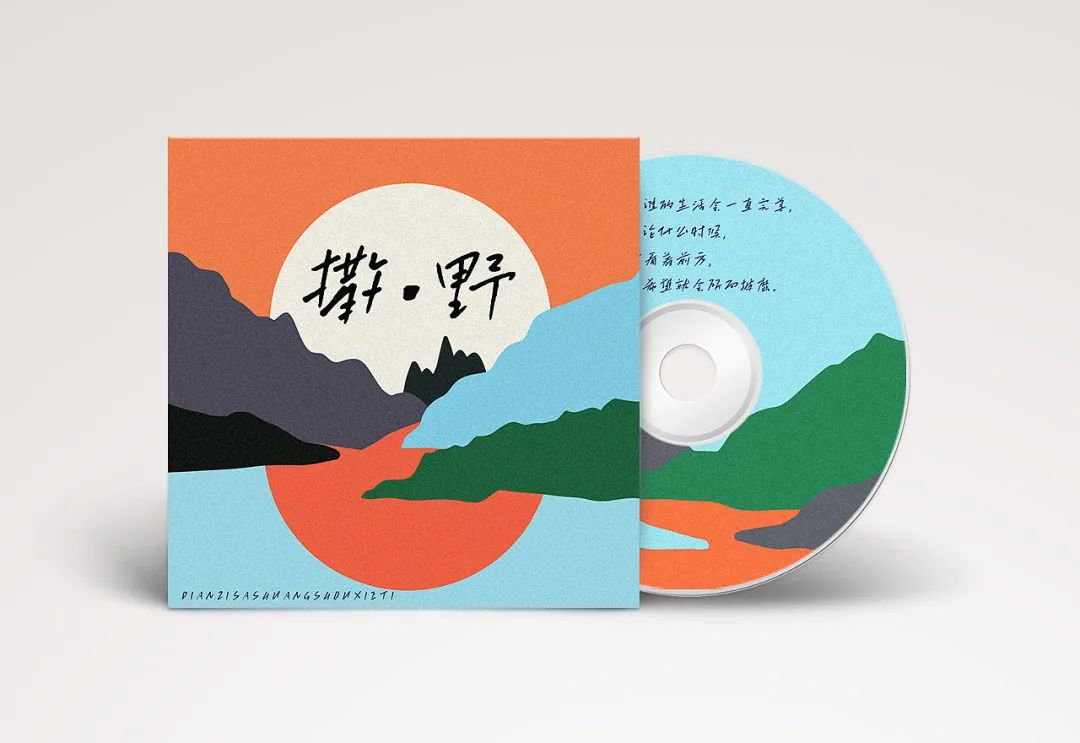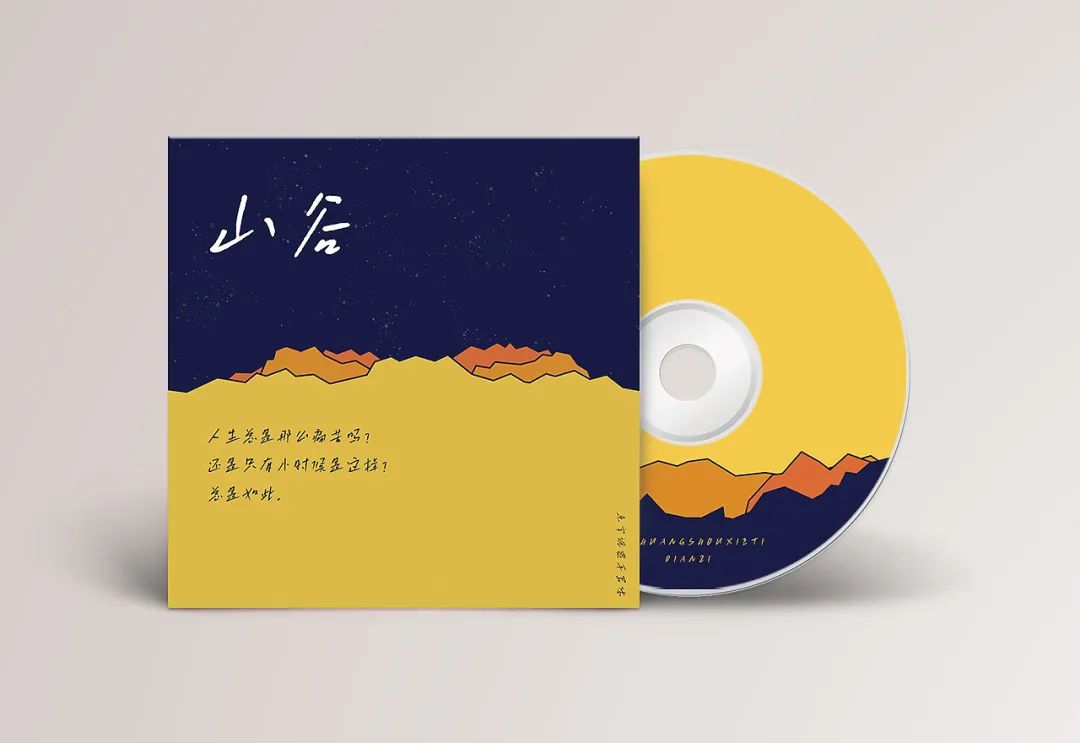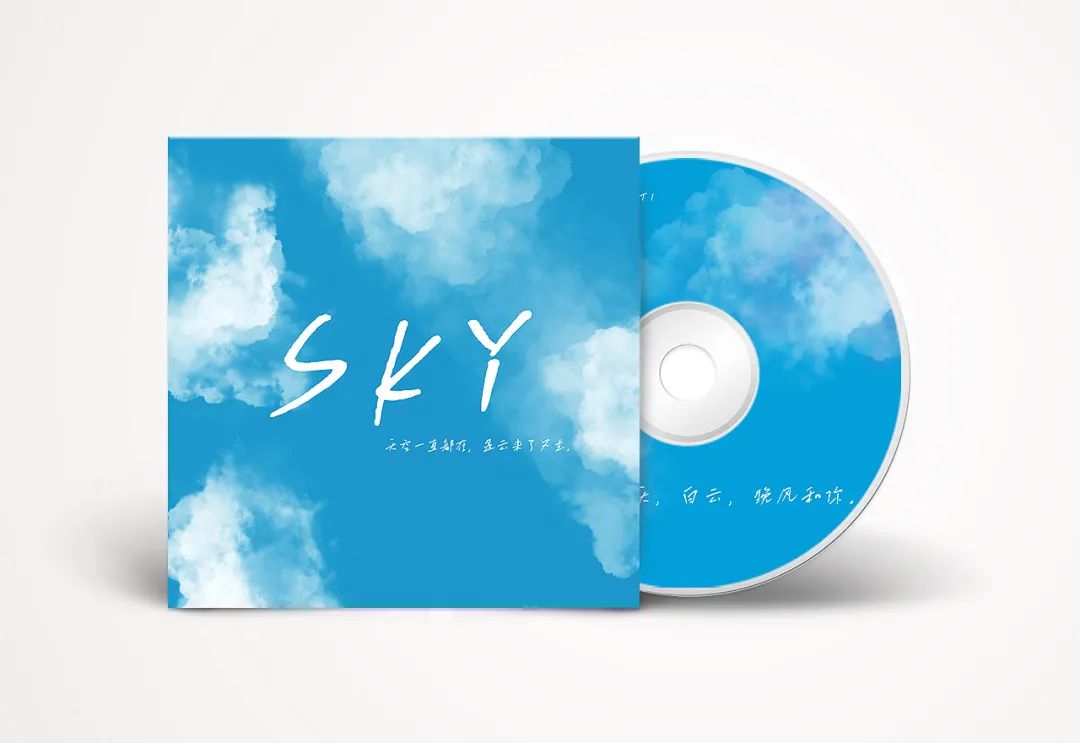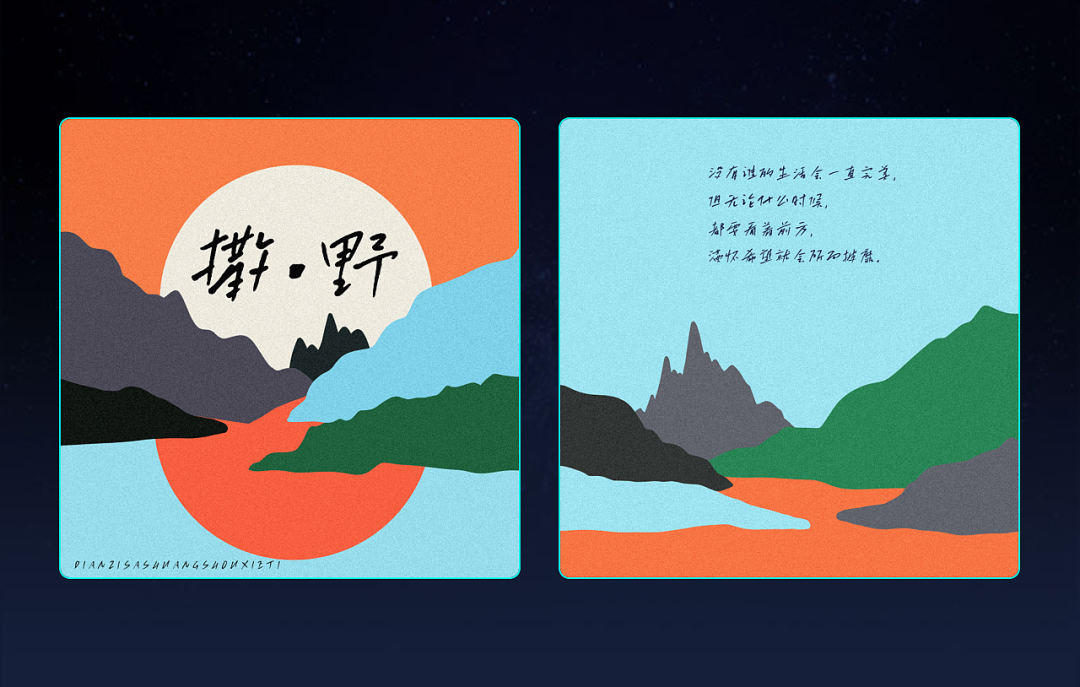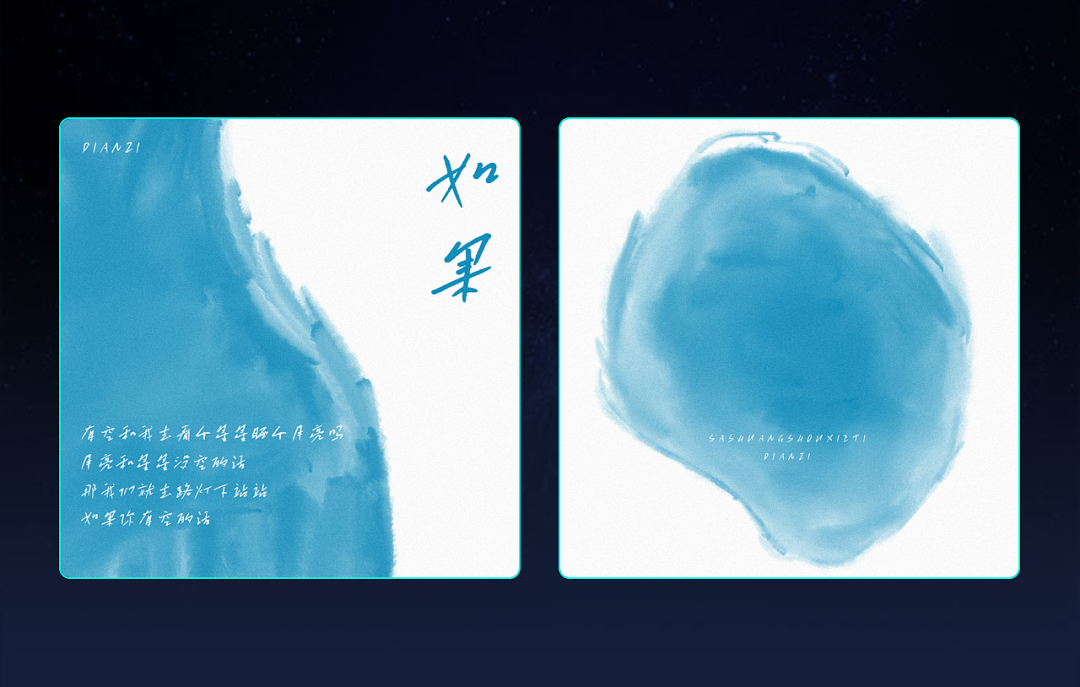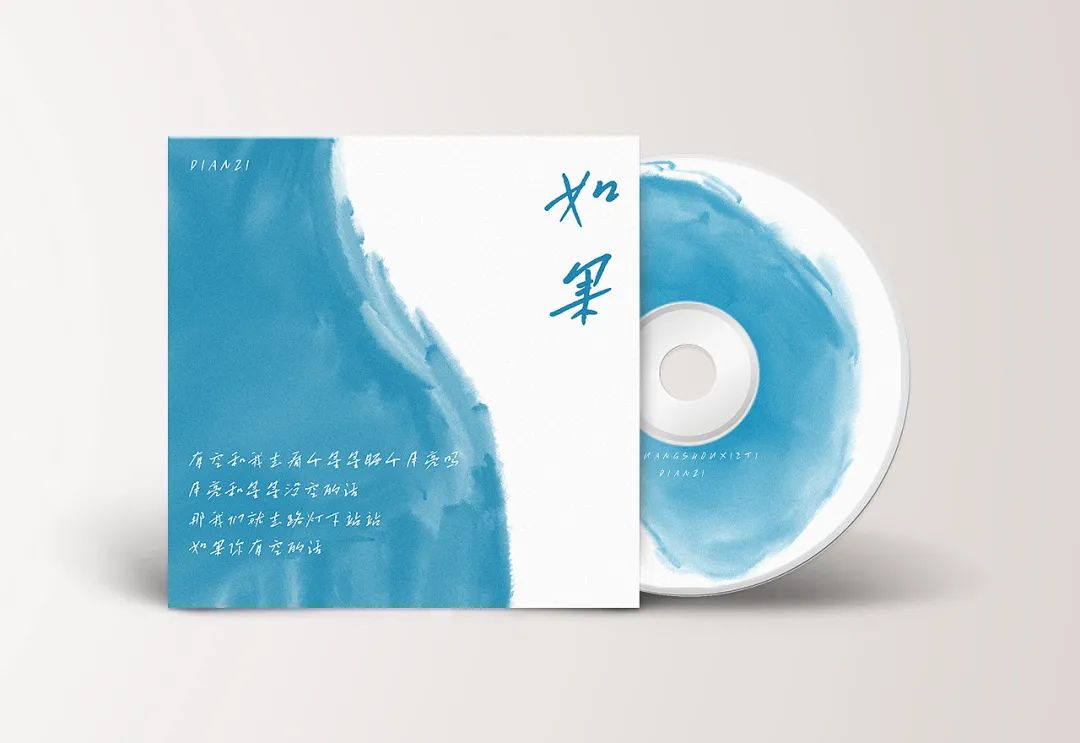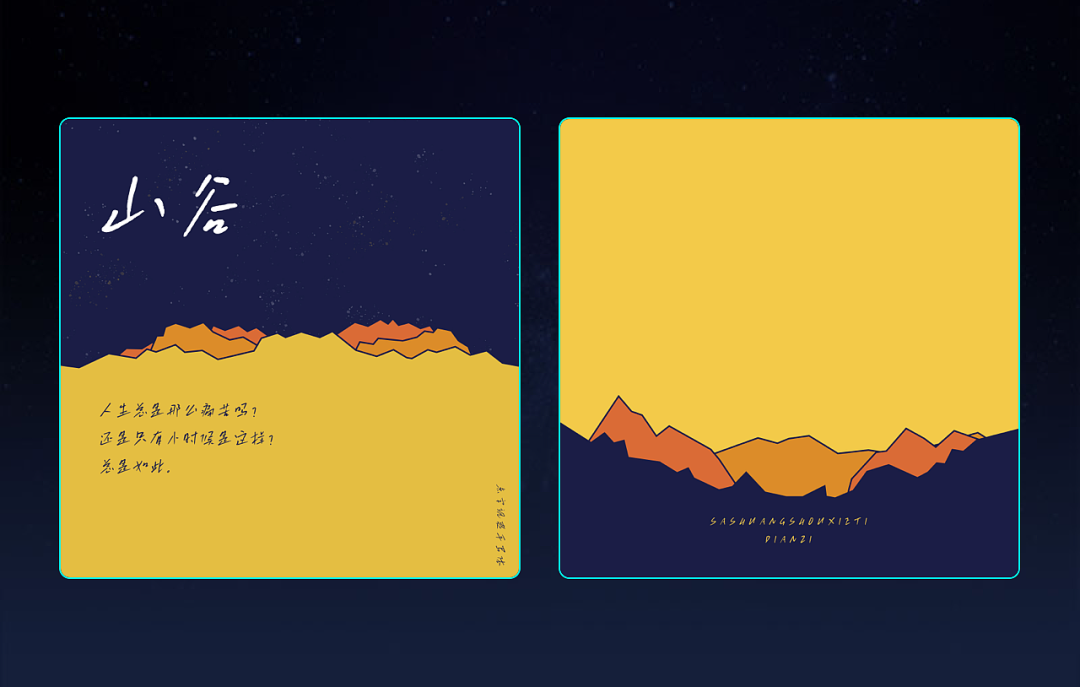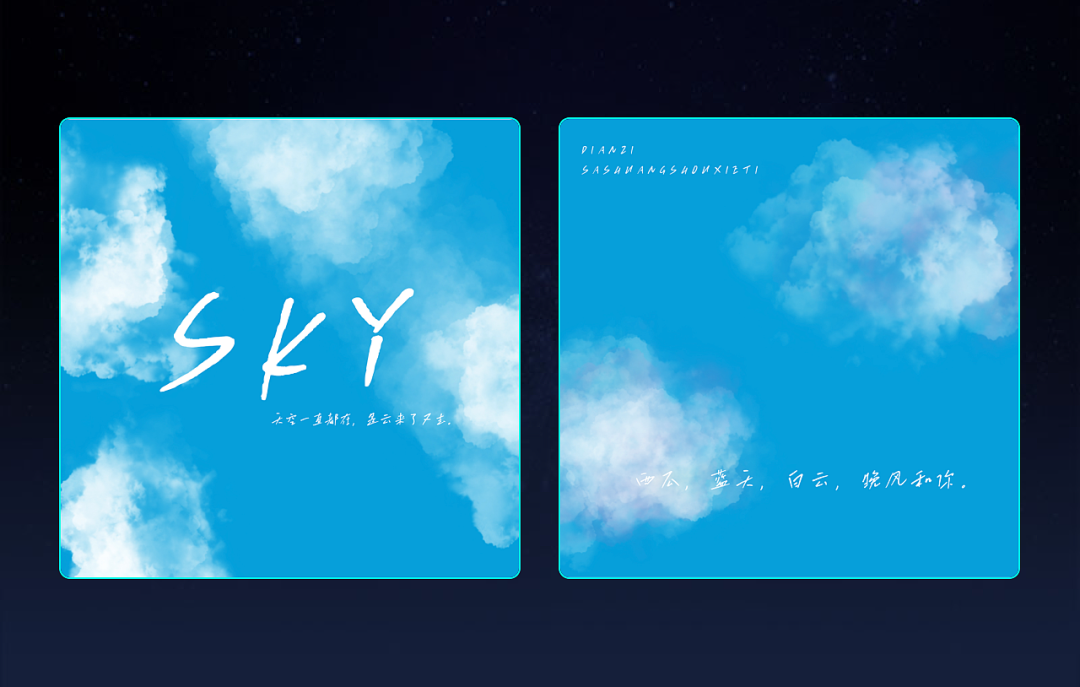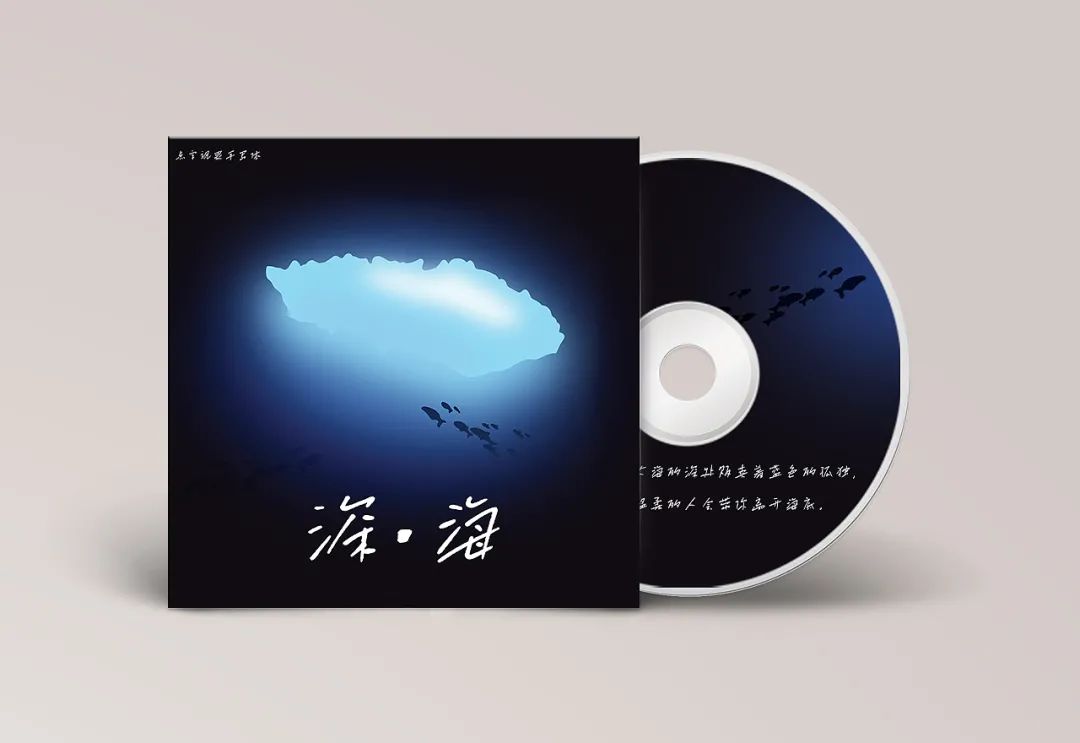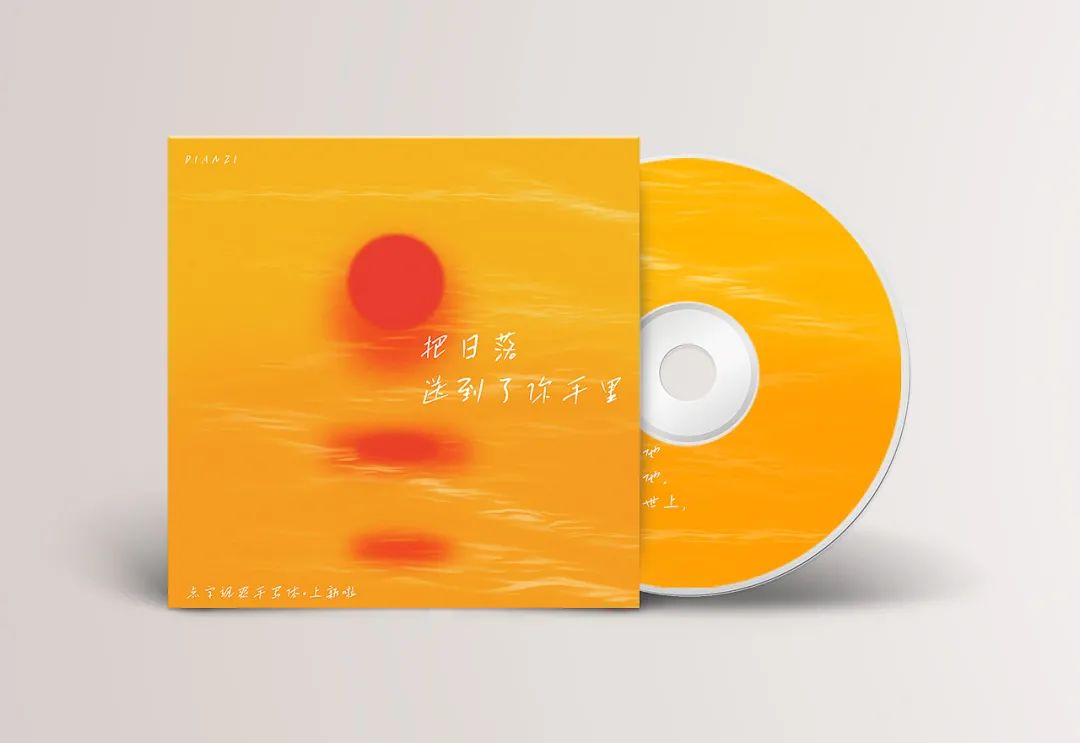
点字飒爽手写体,一款专为音乐而生的字体分享
特别是 重温五月天,突然好喜欢手写字啊!让很多人爱上了这种有个性、有温度,甚至天马行空的手迹感字体。
乍一看,它笔触长如流星穿梭,短如热泪悬眶,结构展如烟花绽放,束如心事深藏。细细观赏,又如你我的青春年华,看似漫不经心,却又余味悠长。
再看看它的实际应用,说它是专为专辑而生,应该不会有人反对吧